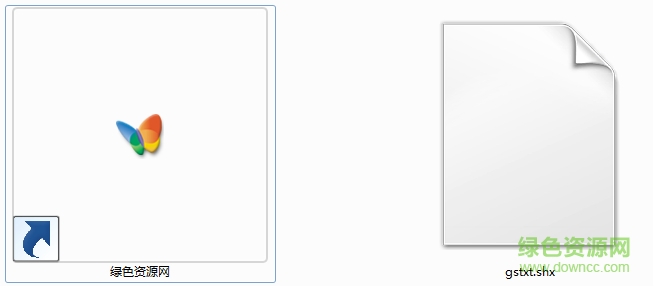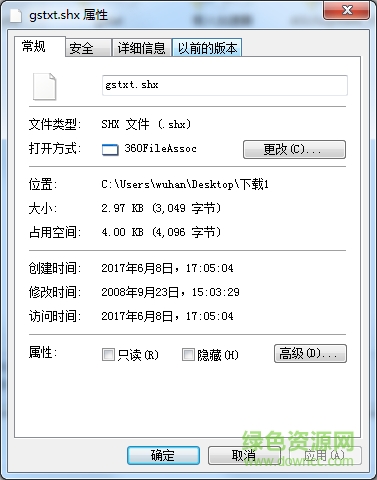
gstxt.shx是在autocad中必不可少的一款字體,此款字體字型端正大方結(jié)構(gòu)簡(jiǎn)潔,當(dāng)電腦中缺少該字體圖紙信息將無(wú)法查看,小編為大家?guī)?lái)了gstxt.shx字的安裝文件和安裝說(shuō)明,歡迎來(lái)綠色資源網(wǎng)下載!